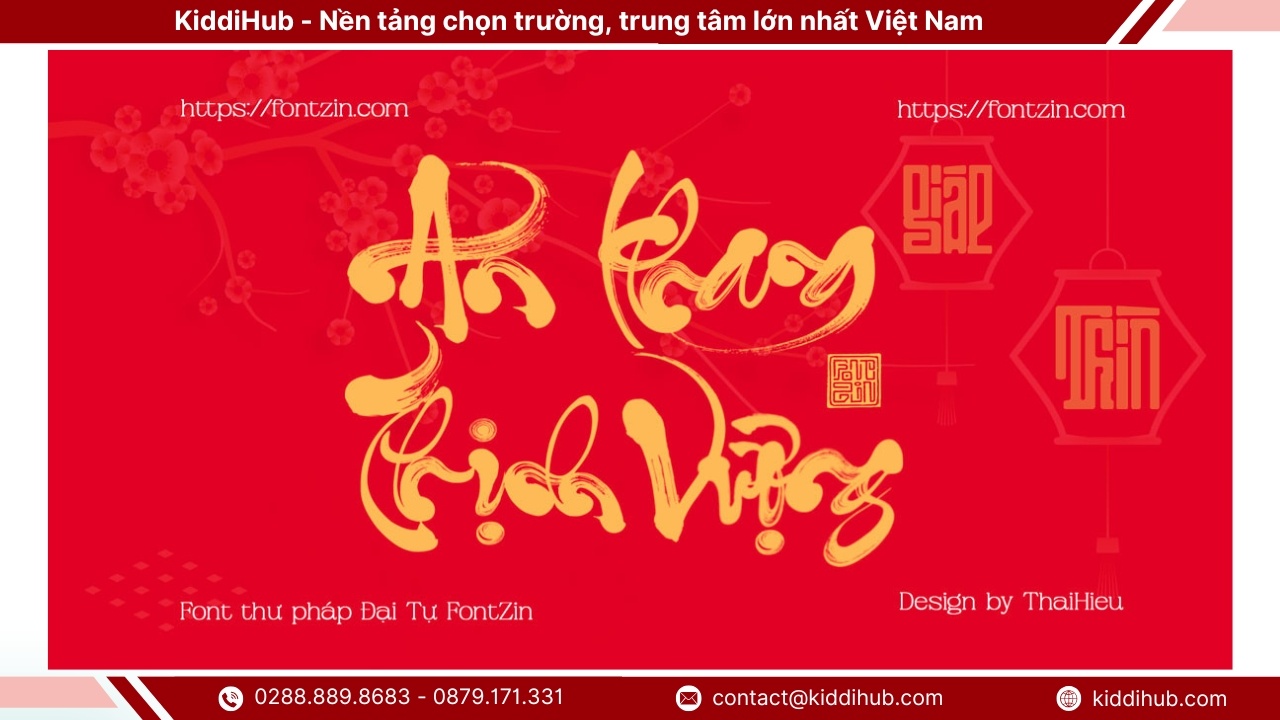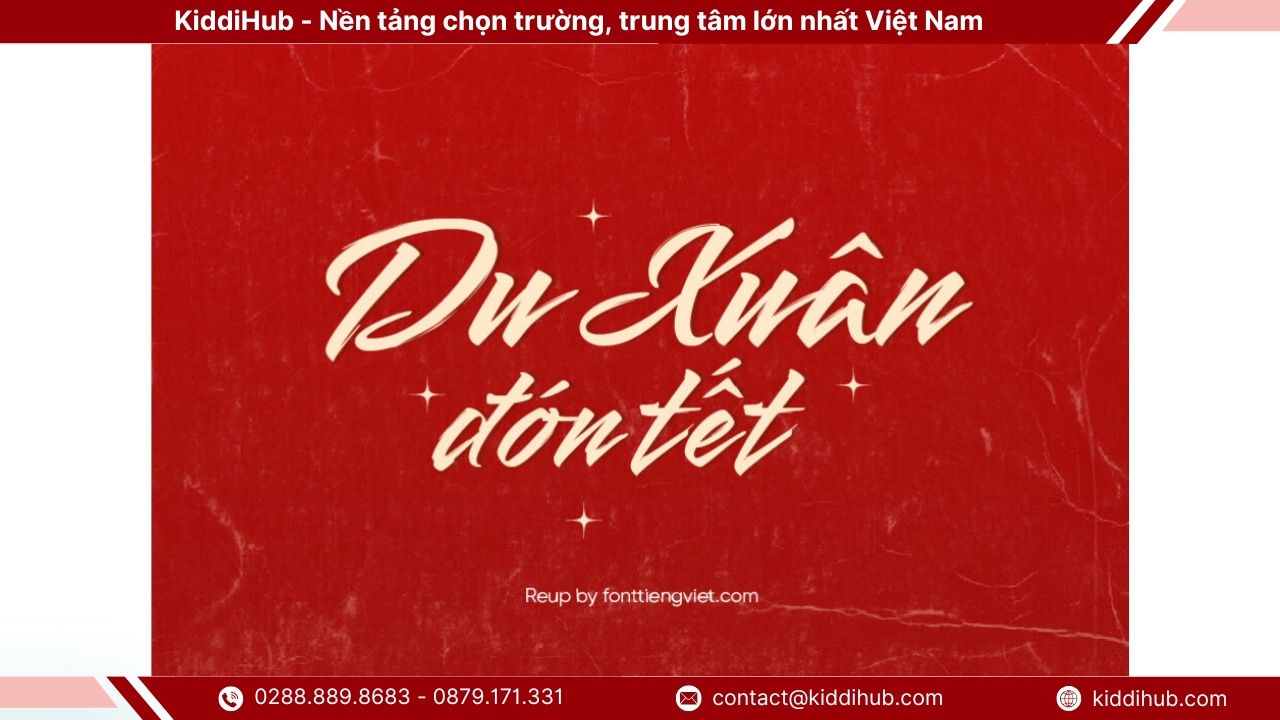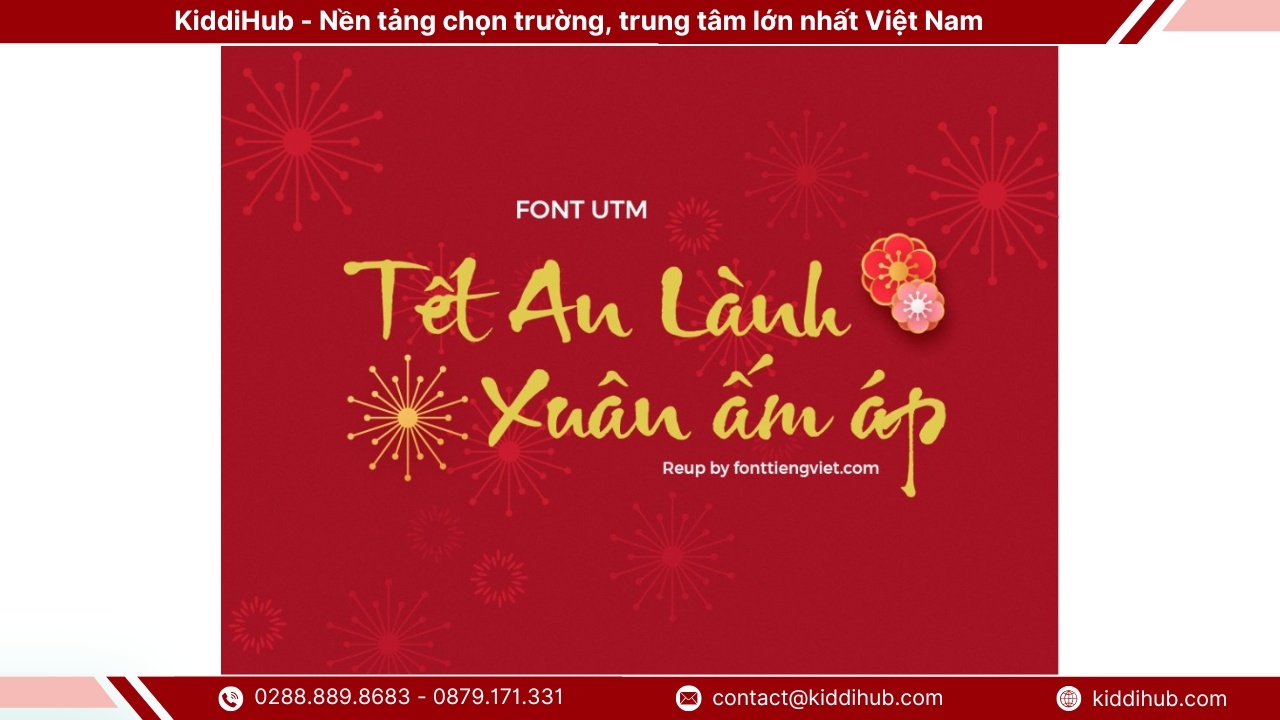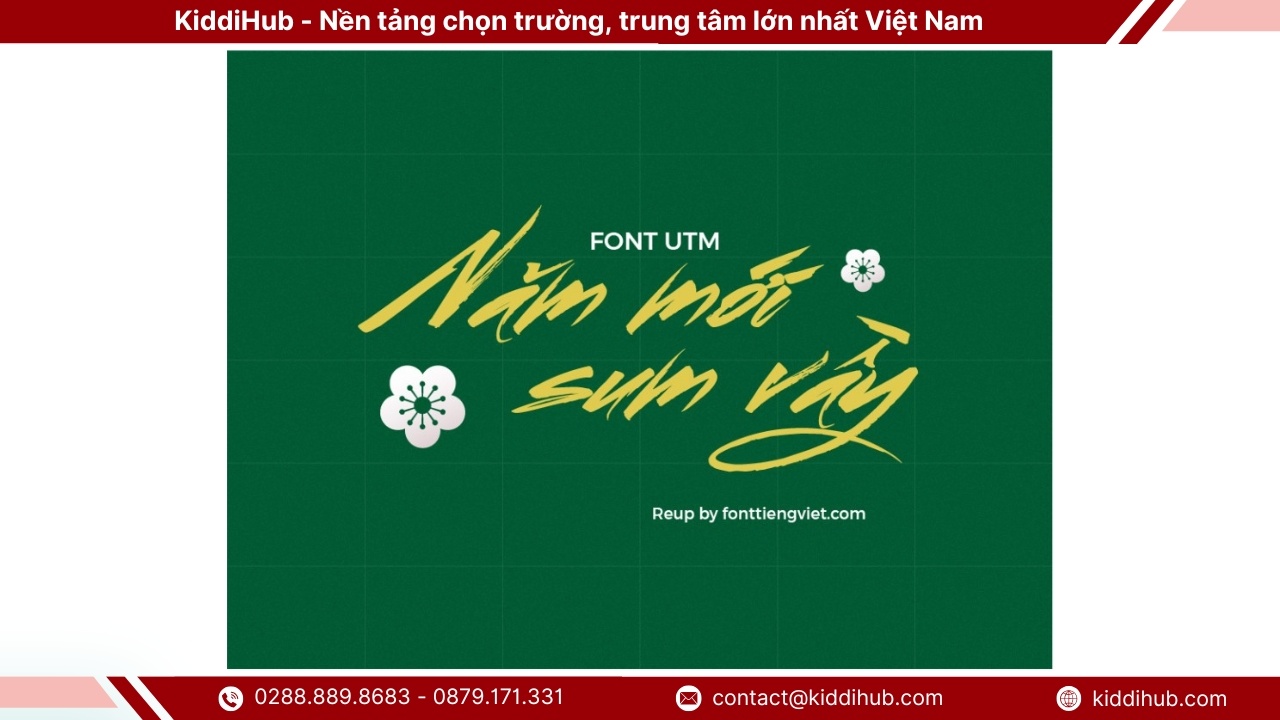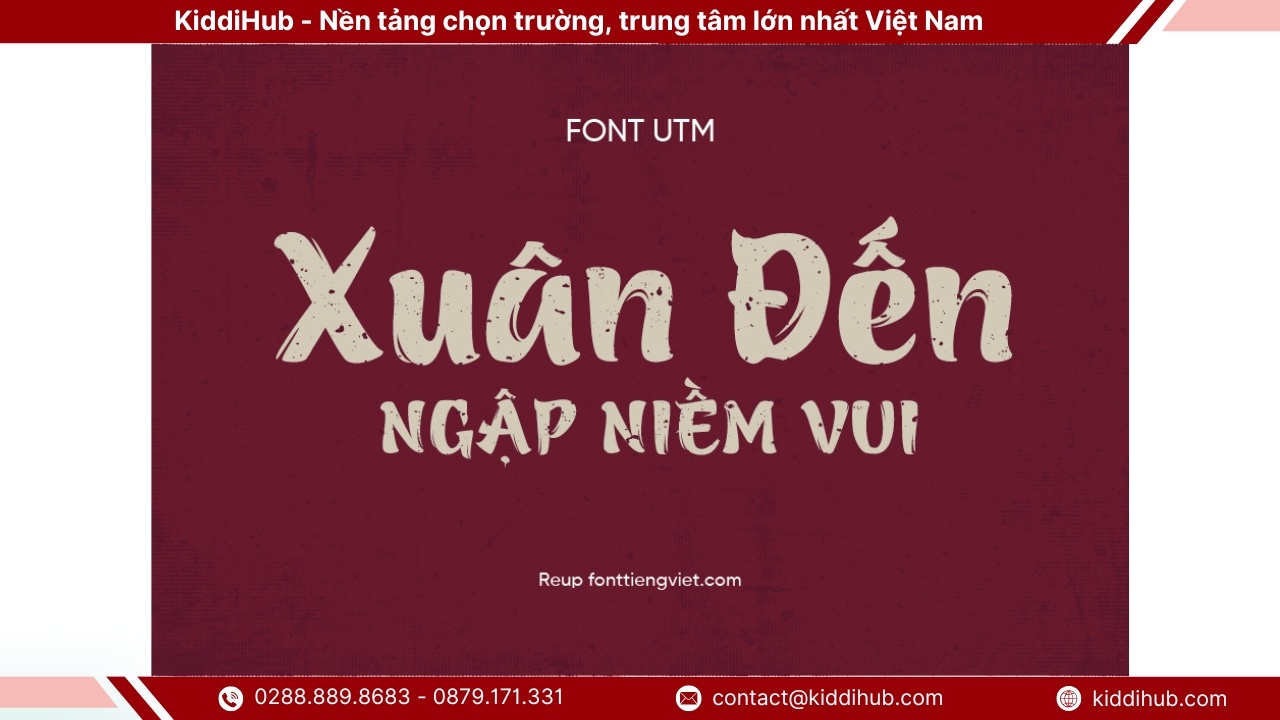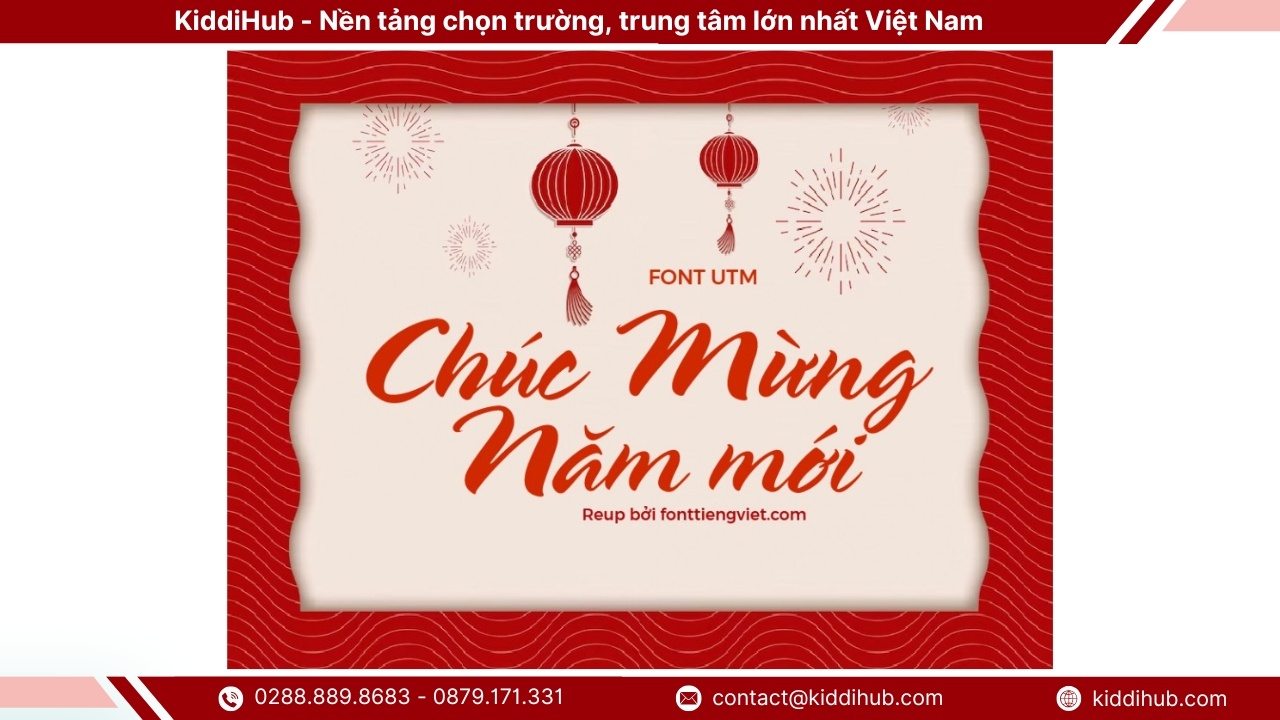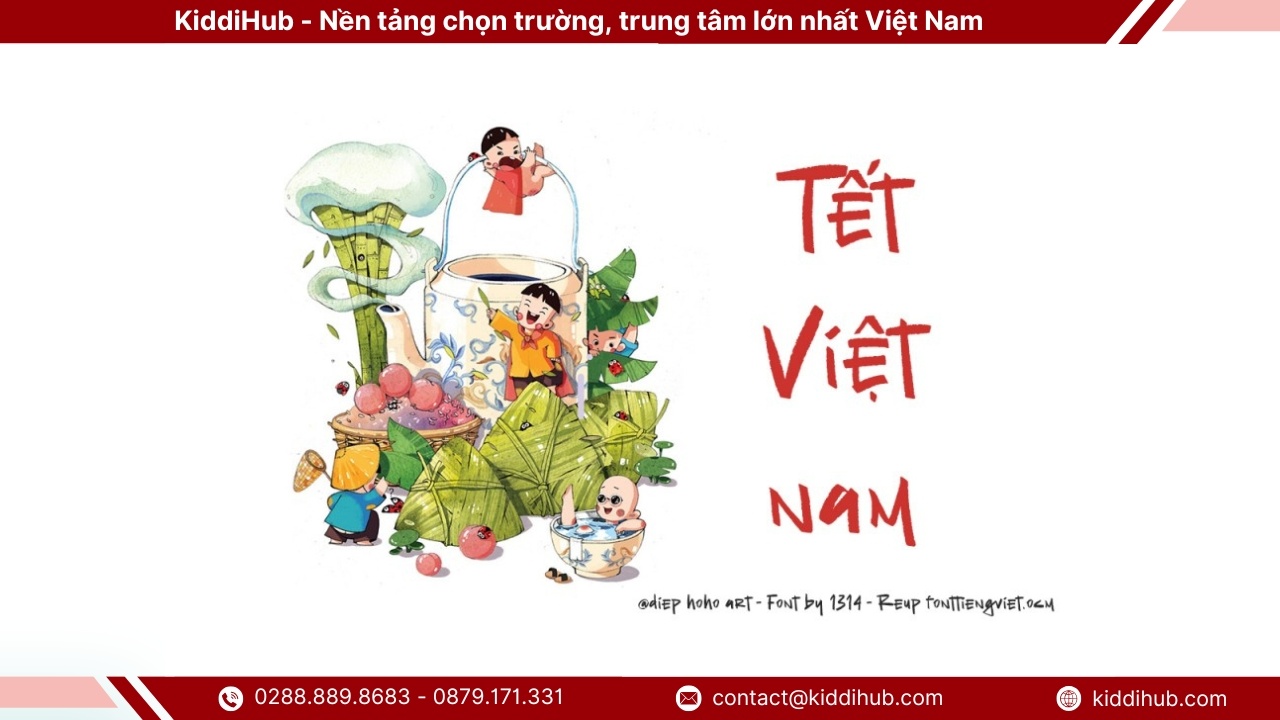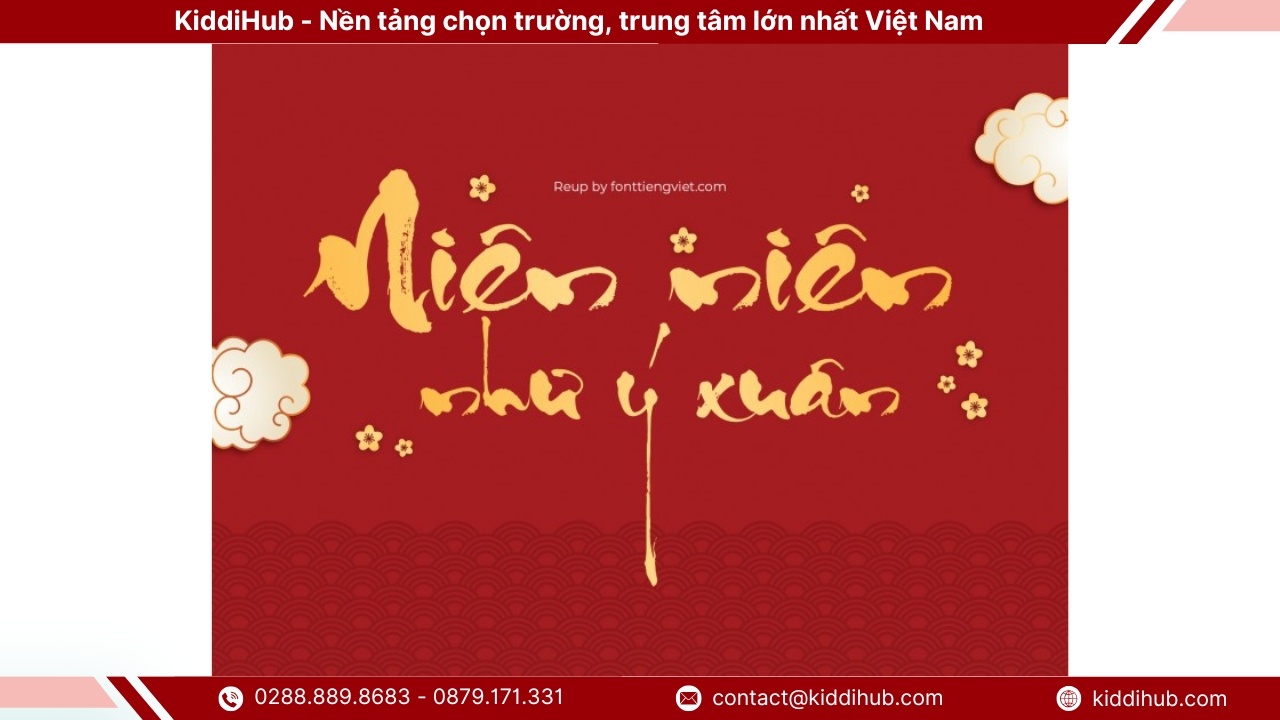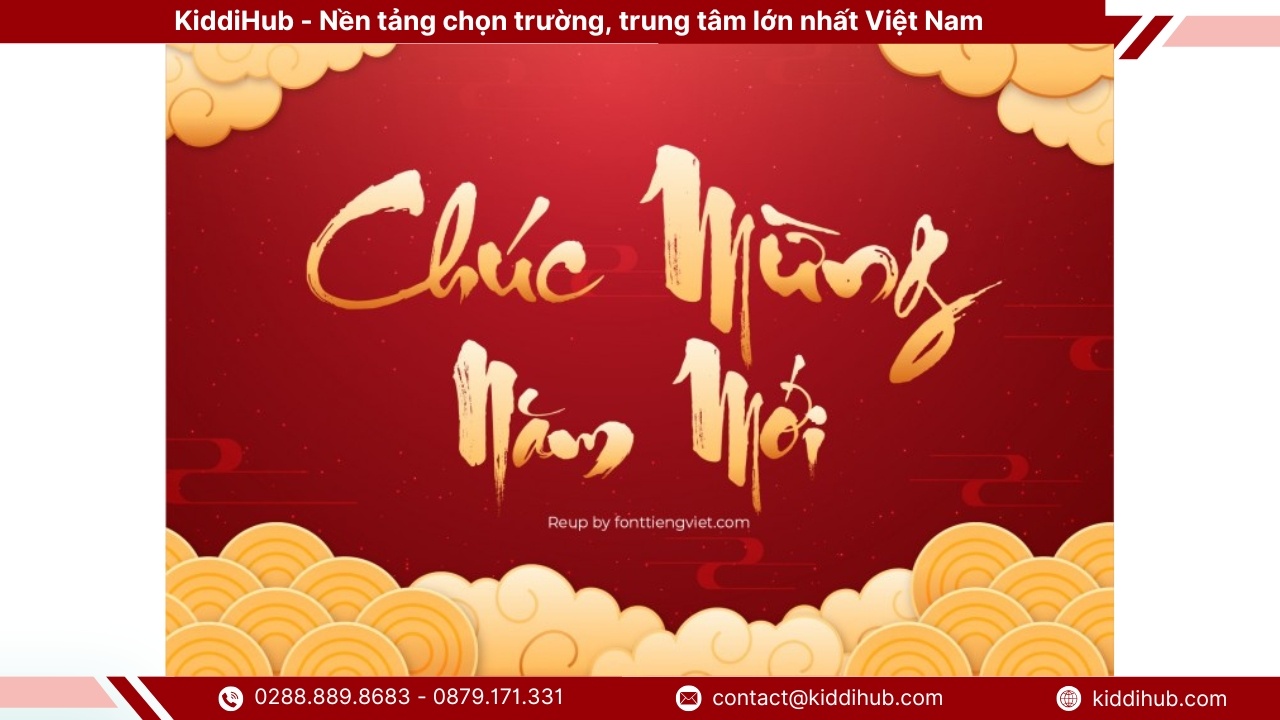
Font chữ thư pháp tết luôn mang đến cảm giác ấm áp, trang trọng và đậm nét truyền thống mỗi khi xuân về. Với những đường nét mềm mại, bay bổng, loại font này giúp các ấn phẩm Tết trở nên sinh động, giàu cảm xúc và ý nghĩa hơn. Trong bài viết này KiddiHub sẽ cùng bạn khám phá và lựa chọn những font chữ phù hợp để làm nổi bật không khí ngày Tết cổ truyền.
Top 20+ font chữ thư pháp Tết đẹp được ưa chuộng hiện nay là lựa chọn lý tưởng cho các thiết kế mang không khí xuân truyền thống. Nét chữ mềm mại, đậm chất nghệ thuật giúp truyền tải trọn vẹn ý nghĩa may mắn, bình an và tài lộc trong dịp năm mới.
Font chữ thư pháp tết Đại Tự được xây dựng dựa trên nét bút thư pháp truyền thống, mang thần thái mạnh mẽ và trang trọng. Kiểu chữ này rất phù hợp để thiết kế lịch Tết, bao lì xì, thiệp chúc mừng, ảnh Tết, áo phông, túi vải, bao bì và logo thương hiệu mang phong cách Á Đông. Bộ font do tác giả Thái Hiếu phát triển với kerning đầy đủ, hỗ trợ ký tự Latin, số, dấu và nhiều ký tự thay thế theo chuẩn Unicode, dễ thao tác trong các phần mềm thiết kế.
Khác với Đại Tự, font thư pháp tết Tiểu Tự thường dùng cho chữ nhỏ nhằm tạo điểm nhấn và cân đối bố cục tranh thư pháp. Nét chữ mềm mại, uyển chuyển, phù hợp trang trí chi tiết, lời chúc ngắn hoặc câu chữ phụ trong thiết kế Tết. Phong cách chữ mang đậm tinh thần thư pháp tiểu tự truyền thống.
Font Smooch mang hơi hướng thư pháp hiện đại, nét chữ tròn trịa và thân thiện. Font hỗ trợ gõ tiếng Việt thuận tiện, thích hợp cho các thiết kế Tết trẻ trung, thiệp chúc xuân và ấn phẩm mạng xã hội.
Font UTM Ông Đồ Già tái hiện hình ảnh ông đồ xưa với nét chữ chậm rãi, cổ kính. Kiểu chữ phù hợp chủ đề Tết truyền thống, hoài niệm và các thiết kế mang không khí xuân xưa.
UTM Ông Đồ Trẻ có nét bút phóng khoáng và tươi mới hơn. Font tạo cảm giác năng động nhưng vẫn giữ được tinh thần thư pháp, phù hợp cho thiết kế Tết hiện đại.
Font mang nét cọ rõ ràng, dứt khoát và cá tính. UTM Brushtip C thường được dùng cho tiêu đề lớn, poster Tết hoặc các ấn phẩm cần điểm nhấn mạnh.
UTM Azuki sở hữu nét chữ mềm mại, dễ đọc, thích hợp dùng cho cả tiêu đề và nội dung trang trí trong các thiết kế Tết nhẹ nhàng.
Font UTM Spring gợi không khí mùa xuân tươi sáng, nét chữ thanh thoát, phù hợp thiệp chúc mừng và banner Tết.
Font mang phong cách cổ điển phương Tây, khi kết hợp với nội dung Tết sẽ tạo điểm nhấn độc đáo và khác biệt cho thiết kế.
Bộ font Thư Pháp Quang Ninh gồm hai kiểu chữ, mang đậm hơi thở thư pháp Việt. Font phù hợp cho nhiều bố cục từ truyền thống đến hiện đại.
Font Thiên An có nét chữ mềm mại, thanh nhã, thường được dùng cho các câu chúc Tết mang ý nghĩa bình an và may mắn.
Font thể hiện tinh thần chúc phúc, thành đạt và khởi sắc đầu năm. Nét chữ rõ ràng, dễ ứng dụng trong nhiều ấn phẩm Tết.
Font chữ thư pháp tết “Công Thủy” mang phong cách thư pháp cổ điển, đậm chất truyền thống, phù hợp tranh chữ và câu đối ngày xuân.
NVN Morning Calm mang nét cổ trang nhẹ nhàng, tạo cảm giác thư thái và trang nhã cho thiết kế Tết Nguyên Đán.
Đây là Font chữ thư pháp tết viết tay tự nhiên, gần gũi, phù hợp thiệp chúc Tết gia đình, trường học và các ấn phẩm mang tính ấm áp.
TLM Bladrimmer sở hữu nét chữ mạnh mẽ, đậm phong cách cổ trang, thích hợp cho poster Tết và tiêu đề nổi bật.
TH Culture gợi nhớ nét chữ xưa, mang màu sắc hoài niệm, phù hợp thiết kế Tết truyền thống và chủ đề ký ức.
Font Đức Thủy mang dấu ấn cá nhân rõ rệt, nét chữ uyển chuyển và nghệ thuật, thích hợp cho tranh thư pháp Tết.
DT Phudu mang phong cách cổ điển, nét chữ mộc mạc, phù hợp các thiết kế Tết mang tinh thần xưa cũ.
Font Stampa gợi lại phong cách chữ thời bao cấp, tạo cảm giác độc đáo và khác biệt cho các ấn phẩm Tết mang màu sắc hoài niệm.
Các phong cách chữ thư pháp Tết phổ biến hiện nay được lựa chọn dựa trên đặc điểm nét chữ và giá trị thẩm mỹ riêng.
Bộ font chữ thư pháp tết sở hữu nét chữ uyển chuyển, giàu tính nghệ thuật, mang đậm hơi thở truyền thống và cảm xúc hoài cổ. Font giúp các thiết kế trở nên tinh tế, khác biệt và dễ tạo dấu ấn riêng. Dưới đây là những đặc điểm nổi bật giúp bộ font này được nhiều người yêu thích và lựa chọn.